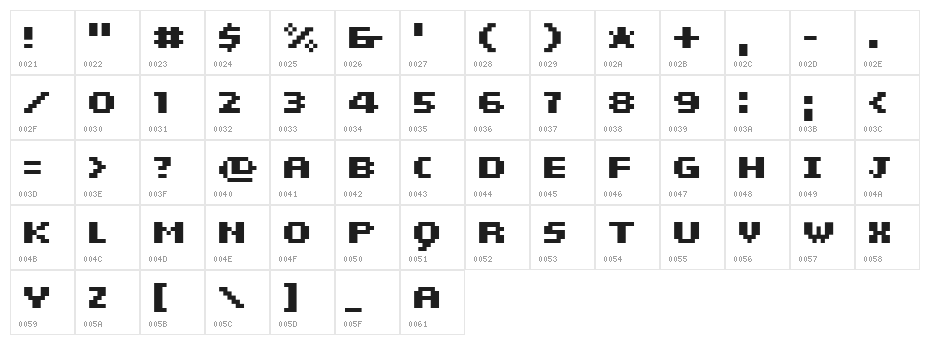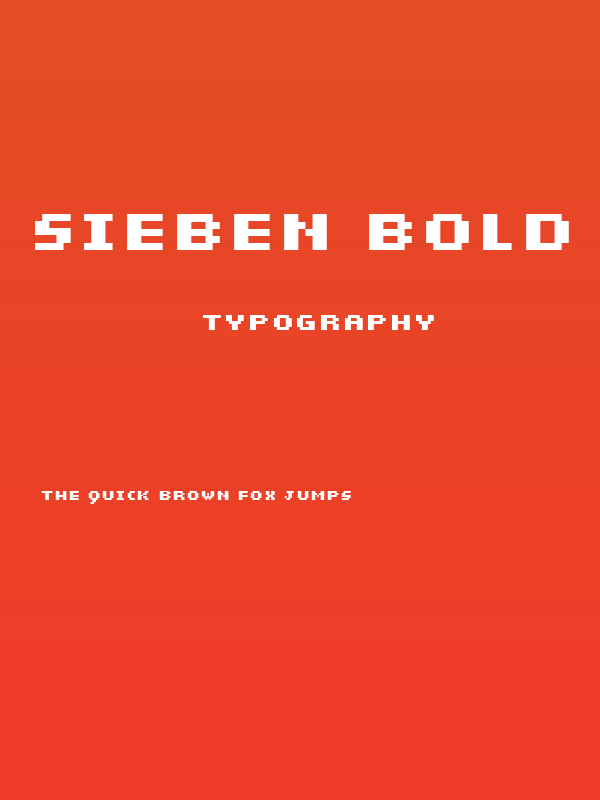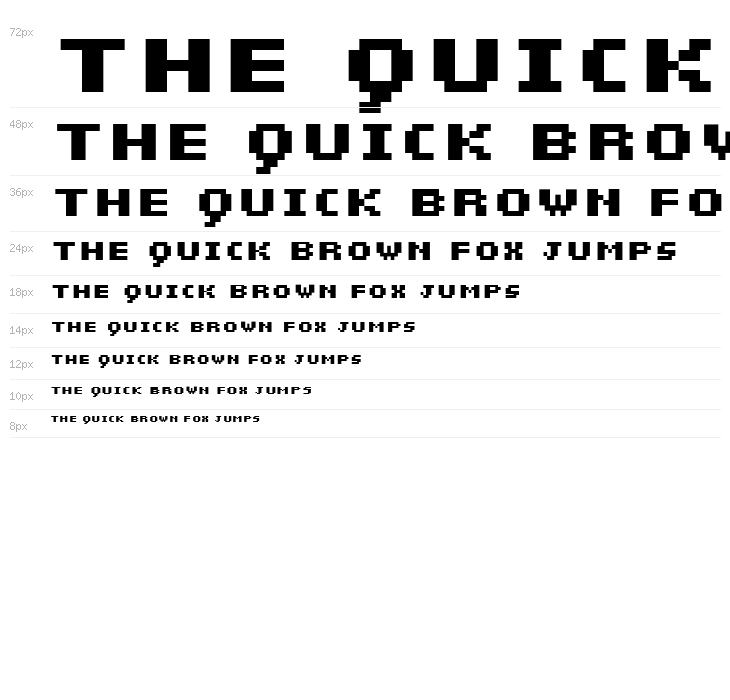
sieben Bold Font
| Estilo geral | Retro, Digital |
| Caso de uso | Headlines, Logos, Digital Art |
| Projetos propostos | Ideal for retro-themed designs, video game graphics, digital art projects, and any creative work requiring a nostalgic, digital look. |